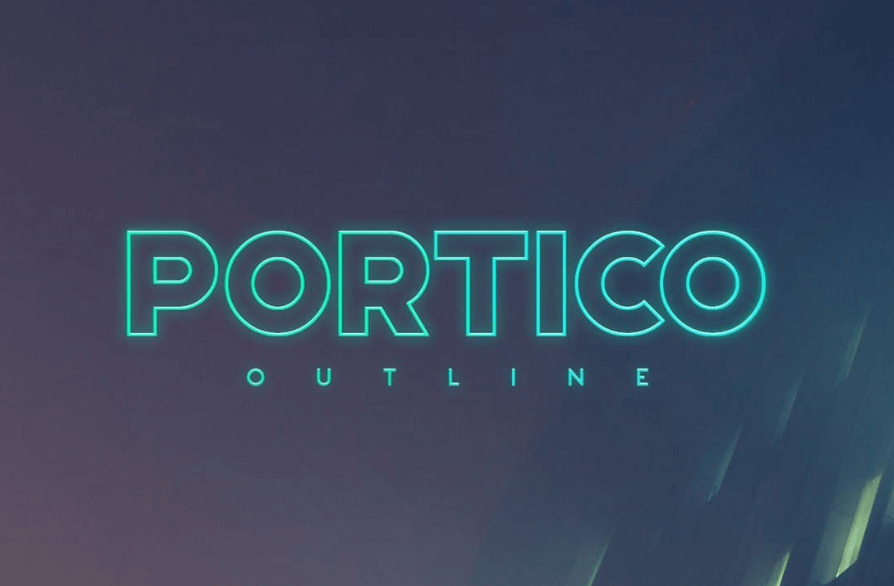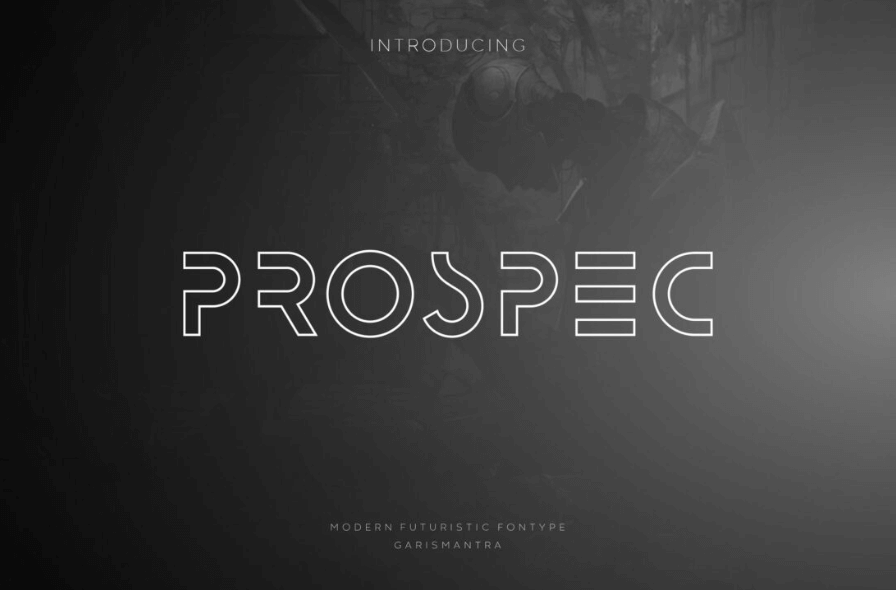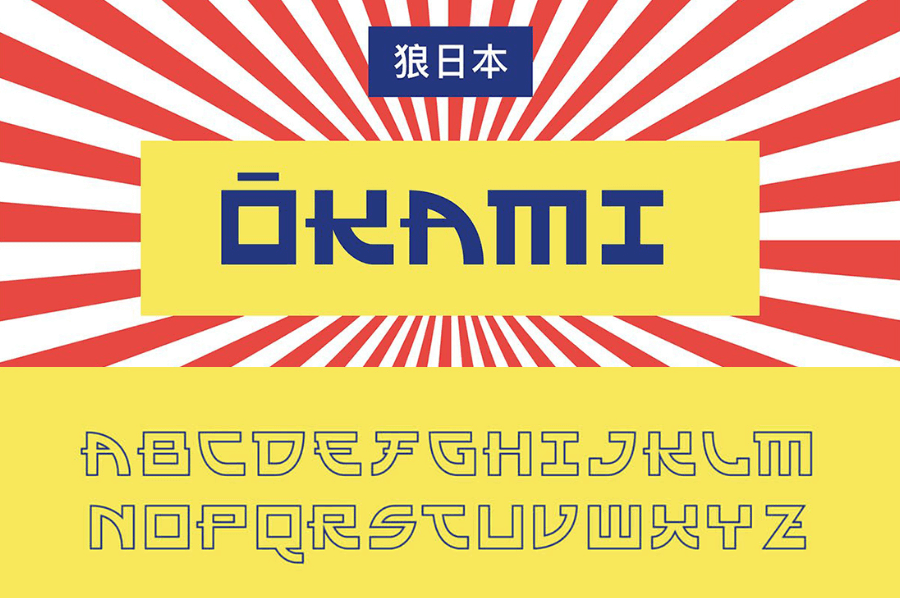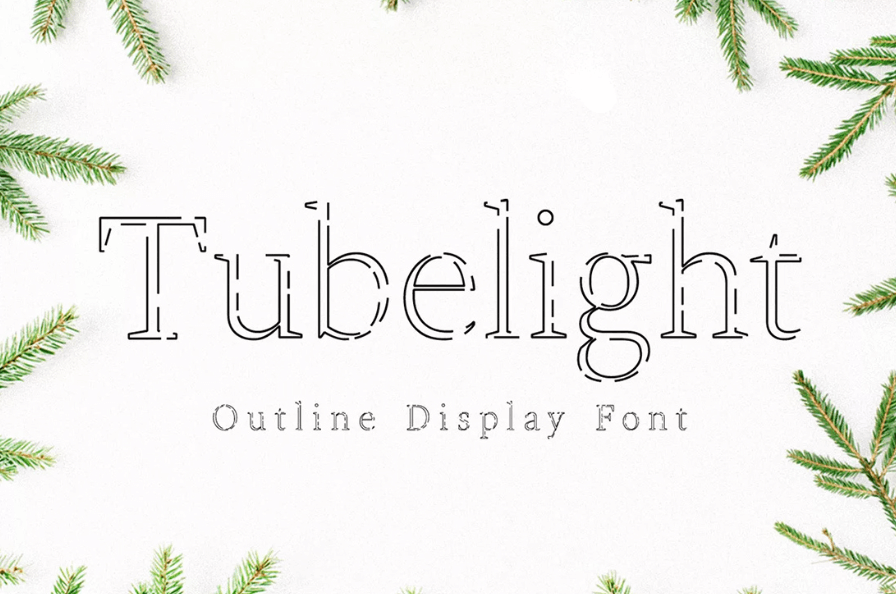
Контурный шрифт — это шрифт, дизайн которого состоит из символов, контура и заливки. Контурные шрифты чаще всего используются для создания заголовков и логотипов. В 1-ой части нашей статьи мы поделились с вами 4-мя советами по использованию таких шрифтов, а в этой части мы представим вам коллекцию лучших контурных шрифтов.
Шрифт Portico Outline — это популярный шрифт в дизайнерском сообществе. Шрифт выделяется своей универсальностью и острой изысканностью. Обладая смелым и угловатым дизайном, у него современный и актуальный стиль букв, который идеально подходит для различного рода проектов от научно-фантастической эстетики до авангардных дизайнов. Эффектнее всего этот шрифт будет выглядеть на заголовков или больших блоках текста, которые требуют внимания.
Prospec — это современный шрифт, который создает огромную адаптивность для широкого спектра дизайнерских проектов. У шрифта контурный стиль с четкой рамкой, которая выделяет буквы и цифры. У шрифта очень стильный и актуальный дизайн, что делает его идеальным выбором для высокотехнологичных проектов, для которых важно создать уникальный и мощный эффект.
Okami — это современный шрифт, дизайн которого отсылает нас к японской эстетике и культуре. Шрифт включает в себя элементы графических японских символов и имеет характерную геометрическую структуру. Okami — это бесплатный контурный шрифт, у которого сдержанные и уникальные формы, которые придают ему яркий характер.
Tubelight — это очаровательный современный шрифт, который можно использовать в любых творческих проектах. Шрифт вдохновлен классическим стилем ар-деко, его дизайн очень изысканный и аккуратный. Шрифт доступен в форматах OTF, TTF и WOFF и содержит прописные, строчные буквы и цифры.